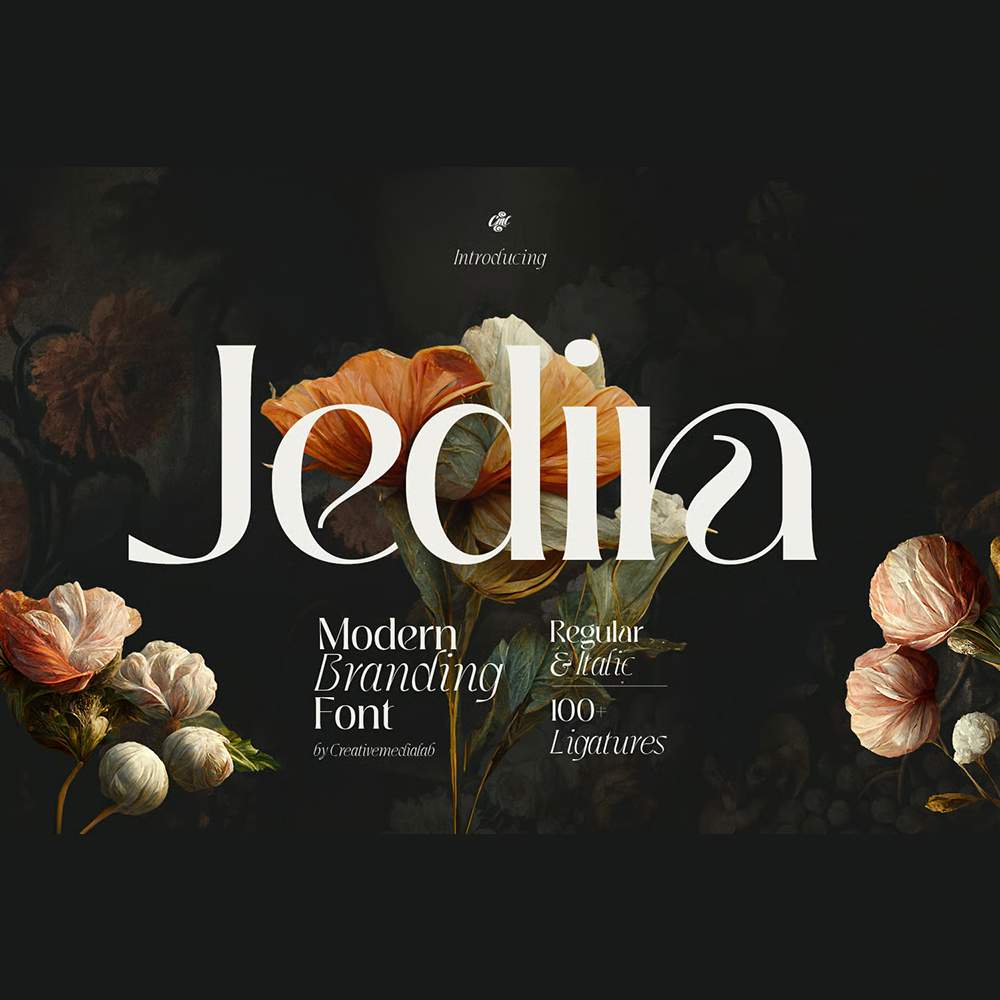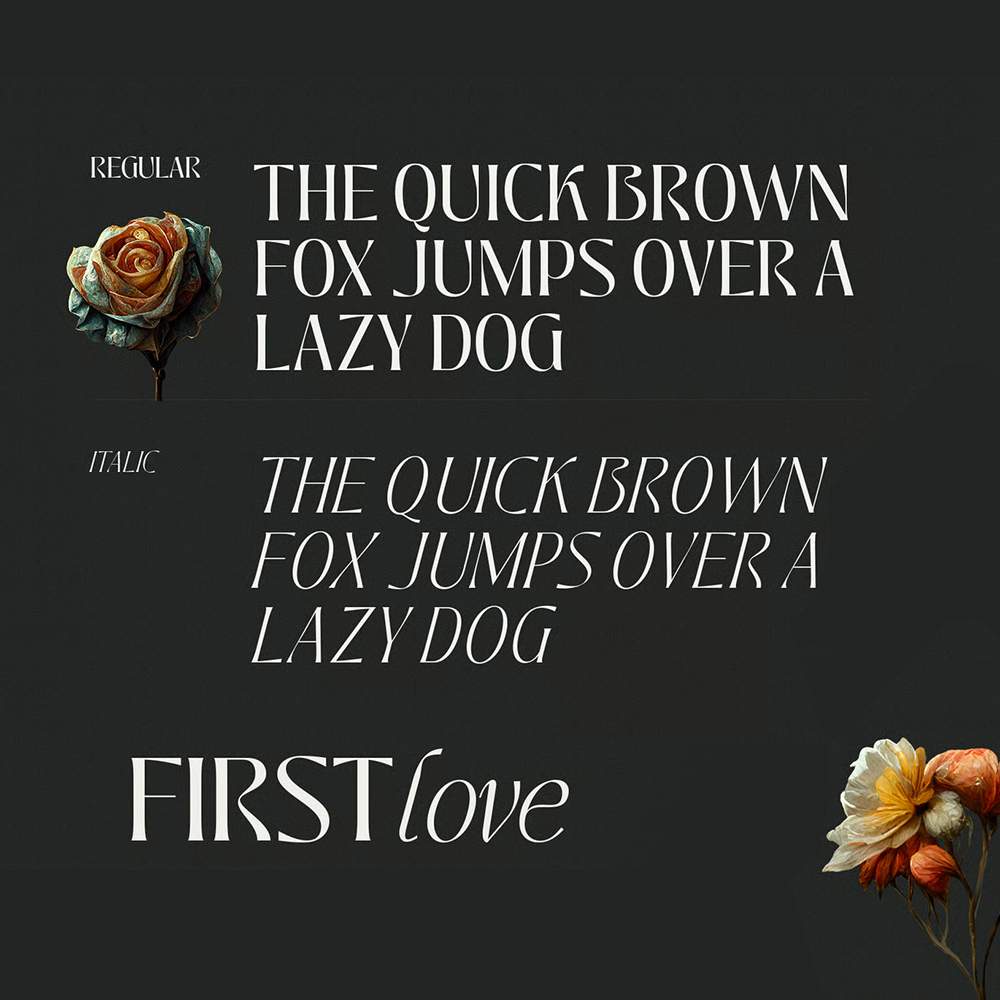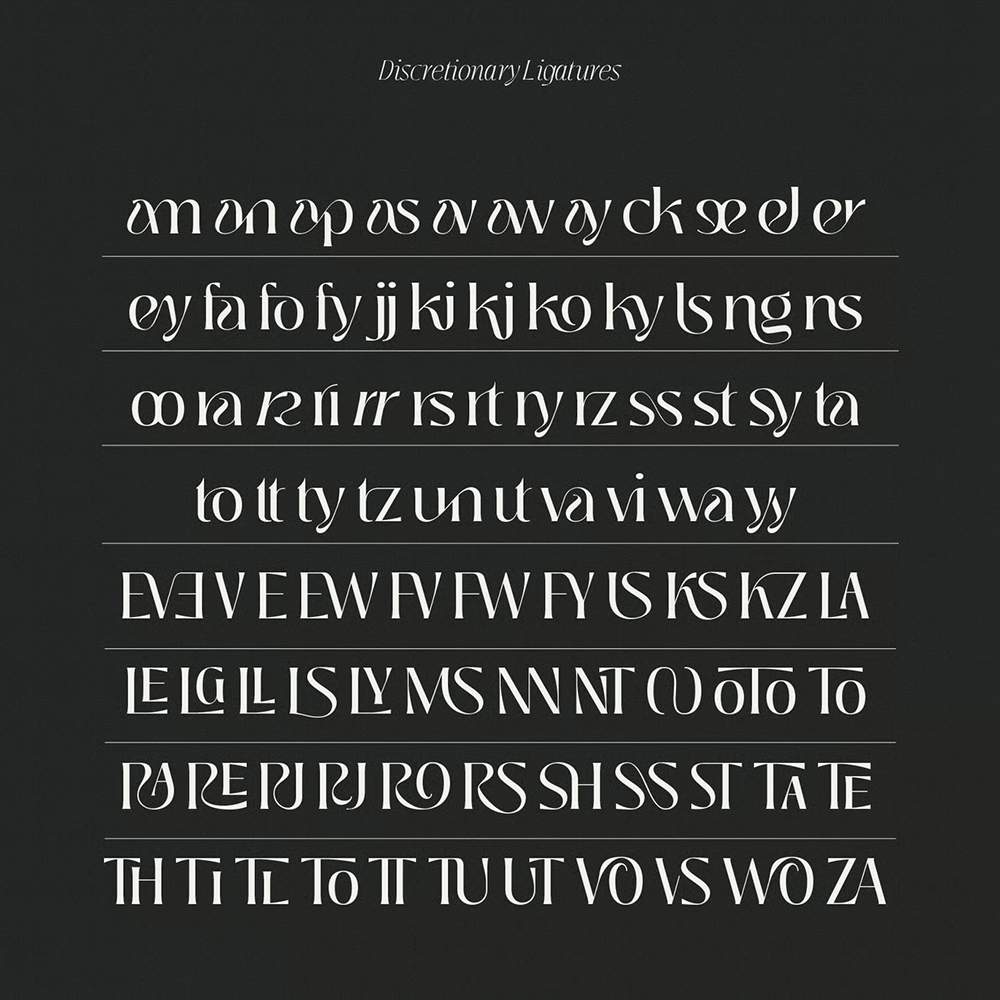
دانلود فونت انگلیسی Jedira Font
فونت پرمیوم و انگلیسی Jedira Font یک فونت نمایشی شیک و زیبا با ایتالیکهای هماهنگ و تعداد زیادی لیگاتور است. این فونت همهکاره برای برندسازی، پروژههای طراحی وب، لوگوها، مفاهیم مرتبط با مد و موارد دیگر ایدهآل است.
مزایای استفاده از فونت لاتین Jedira چیست؟